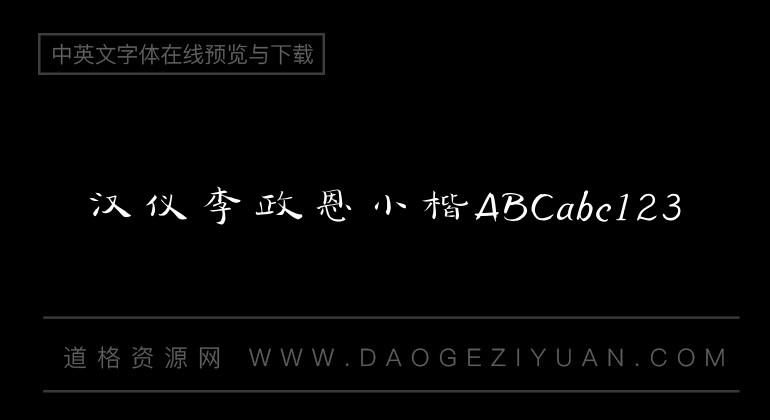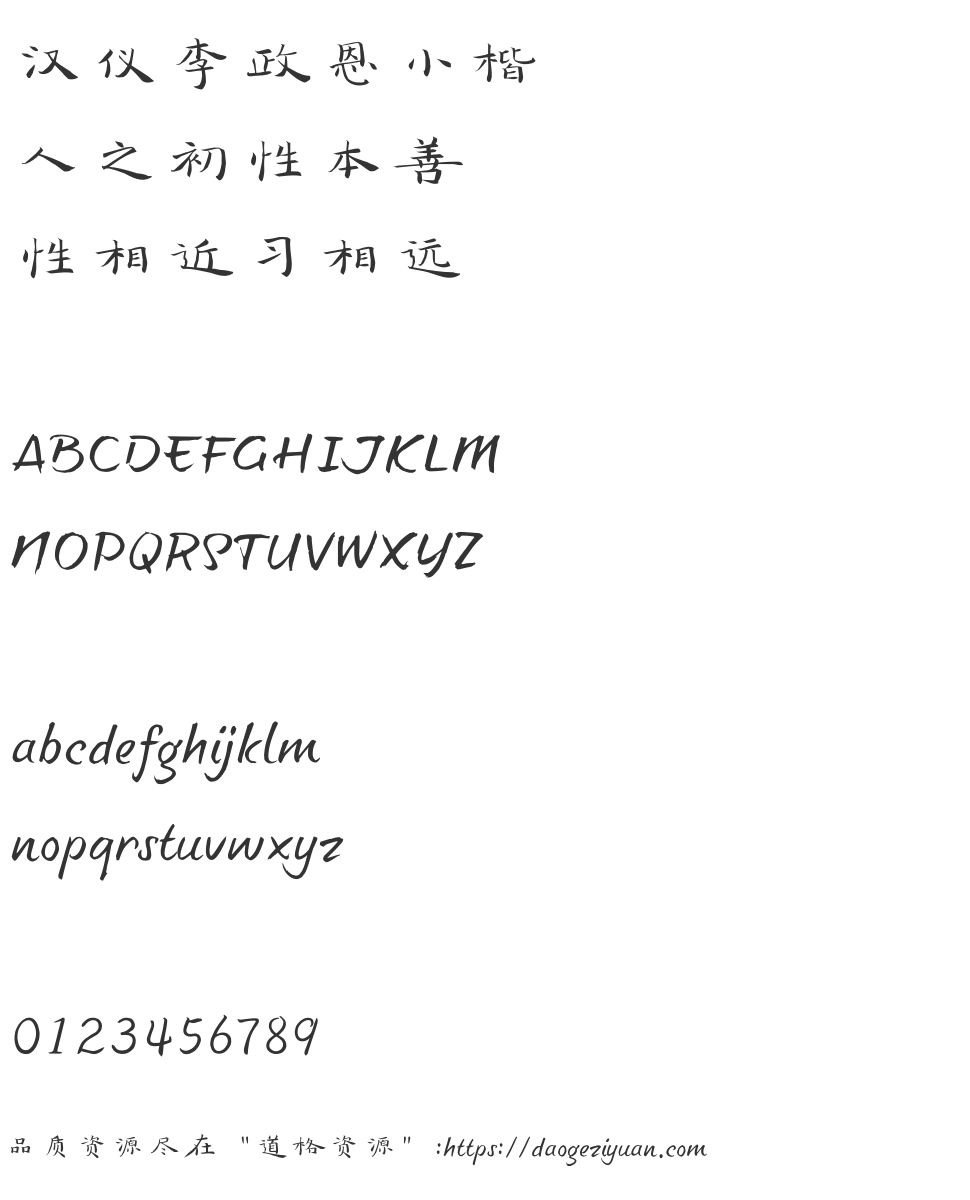
汉仪李政恩小楷字体是一种优秀的中文书法字体,由汉仪字库设计师李政恩先生亲自设计完成。这款字体的特点在于它的线条流畅自然,笔画有节奏感,且字形优美端庄。 汉仪李政恩小楷字体的设计灵感源自传统中国书法,但在细节处理上更加精致。字体采用了古法纸张墨迹的质感,给人以历史感和文化底蕴的感受。同时,为了适应现代数字化排版的需要,这款字体也进行了技术上的优化,使得其在各种应用中都有很好的表现。 总的来说,汉仪李政恩小楷字体是一款非常优秀的中文书法字体,它融合了传统和现代的设计理念,具有很高的美感和艺术价值。在印刷、广告、媒体等各个领域都有广泛的应用。文件名:汉仪李政恩小楷
汉仪李政恩小楷是一款非常不错的手写艺术字体,具有很好的视觉感,适合于文化类的宣传设计、商业类品牌的广告和产品包装设计以及个性化文字排版等较多场景。